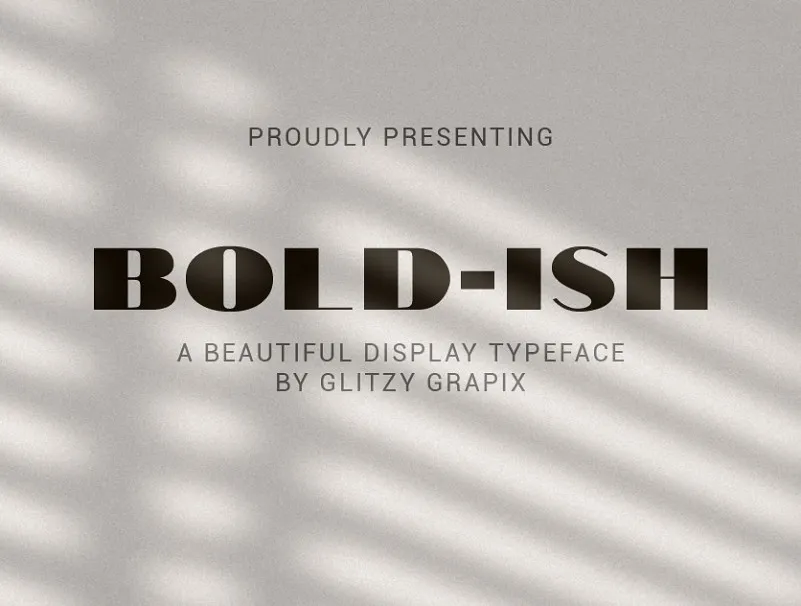
Esta é uma fonte ‘Sans Serif’ chamada Bold-ish, criada por Lelanie De Lange. Ela é moderna e elegante, com um grau de boldness que faz do Bold-ish uma escolha impecável para usar em headlines e títulos. Suas qualidades simples tornam o tipo atraente para diversos usos, como logotipos, anúncios, camisetas, cartões de visita, painéis, etiquetas, selos e muito mais. Ideal tanto para ambientes digitais quanto físicos, Bold-ish é uma ótima escolha para aqueles que desejam um tipo moderno e sofisticado. Sua simplicidade permite que ela se destaque em qualquer formato de design gráfico.